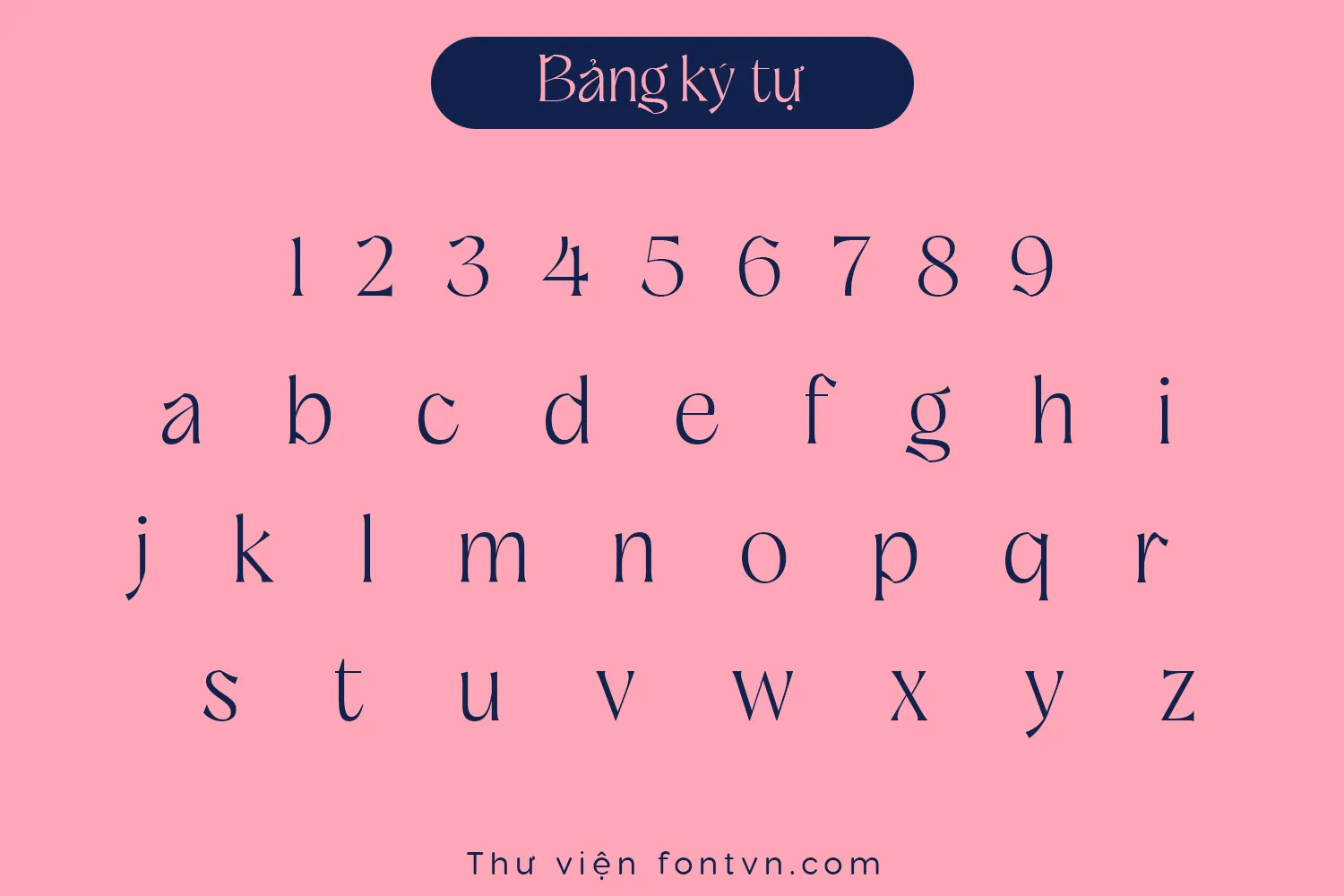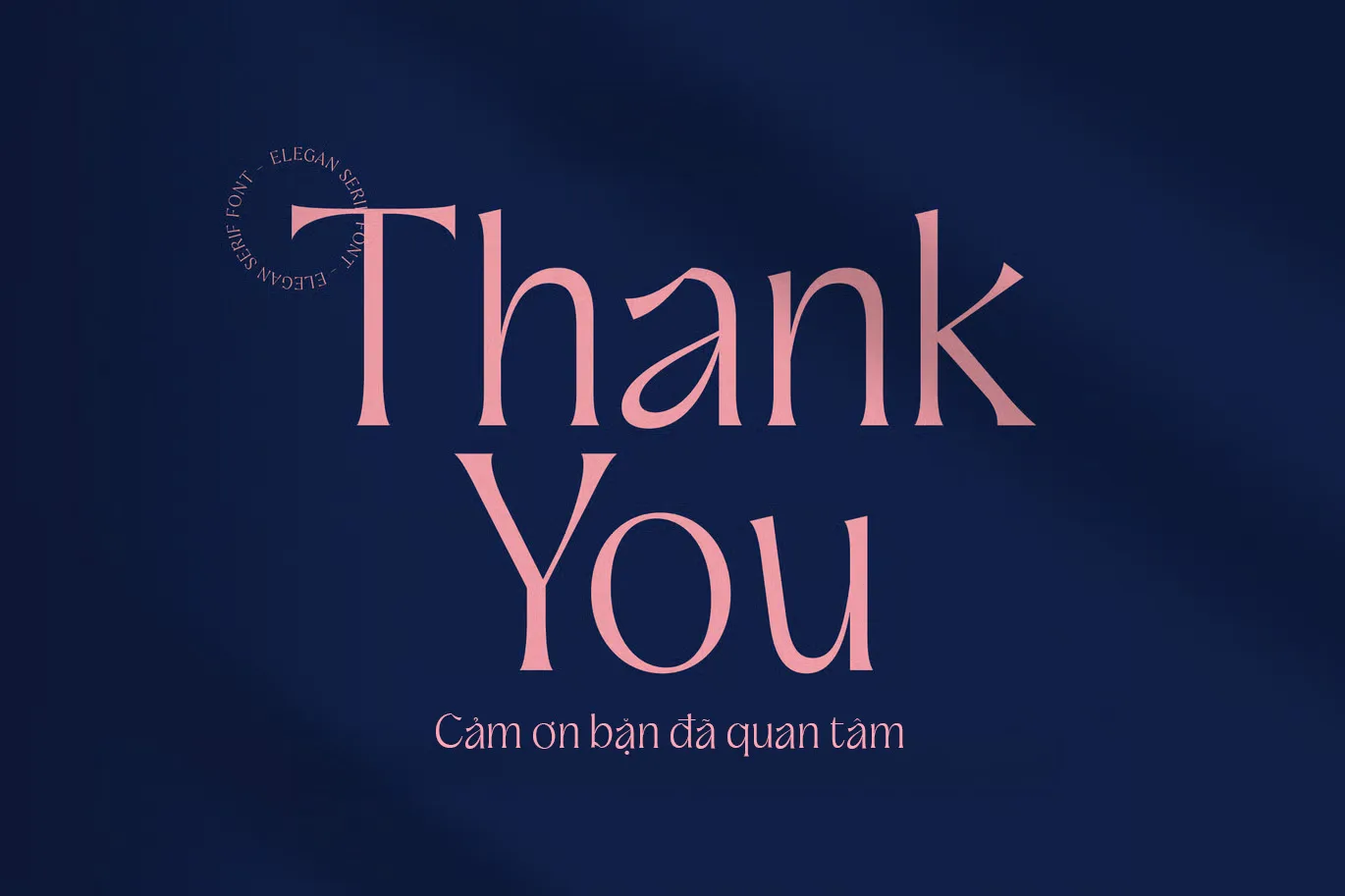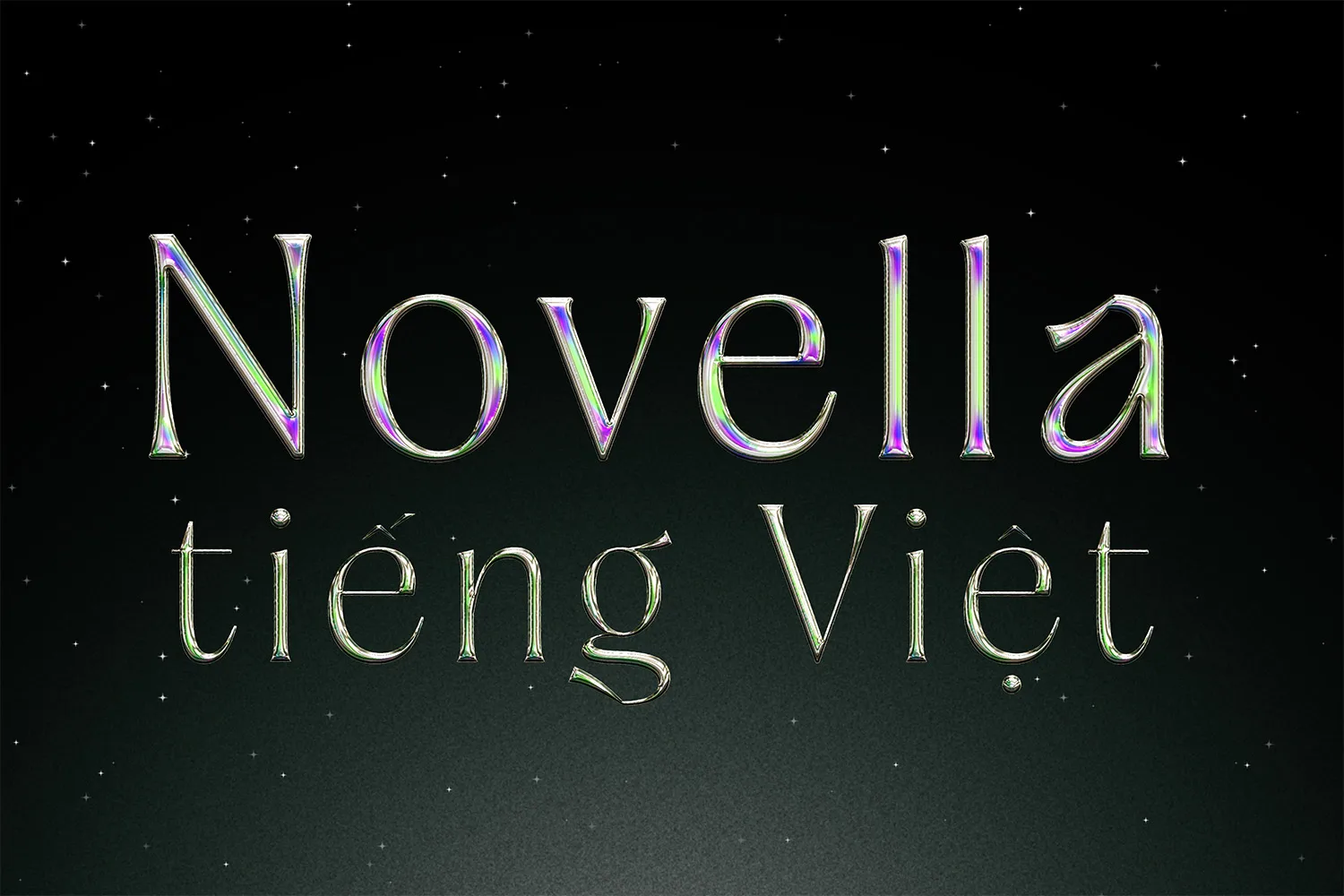
DVN Novella tiếng Việt – Font chữ Serif sang trọng và tinh tế
DVN Novella là một typeface thuộc nhóm display serif, đặc trưng bởi độ tương phản (contrast) cực kỳ cao giữa các cấu trúc nét. Thiết kế tập trung vào sự sắc sảo thông qua các nét chính (stem) thanh mảnh và nét phụ (hairline) tối giản, kết hợp cùng hệ thống chân chữ (serif) dạng dẹt, cắt gọt dứt khoát. Tổng thể font được xây dựng trên trục thẳng đứng (vertical axis) chặt chẽ, cùng không gian âm (negative space) mở rộng ở các ký tự dạng vòm, tạo nên một diện mạo thanh lịch, tĩnh tại và mang đậm tính hình học chuẩn xác.
Về mặt ứng dụng, cấu trúc siêu mảnh của DVN Novella đòi hỏi font phải được sử dụng ở các kích thước hiển thị lớn để phô diễn trọn vẹn các chi tiết hairline. Đây là công cụ typographic tối ưu cho các dự án yêu cầu tính sang trọng, chẳng hạn như thiết kế nhận diện thương hiệu cao cấp (luxury/fashion branding), thiết kế logotype, bìa tạp chí (editorial design) hoặc các tiêu đề (headline) khổ lớn. Ngược lại, thiết kế này không được khuyến nghị để dàn trang cho các đoạn văn bản dài (body text) hoặc sử dụng ở kích thước hiển thị nhỏ vì sẽ làm giảm đáng kể khả năng đọc (legibility).